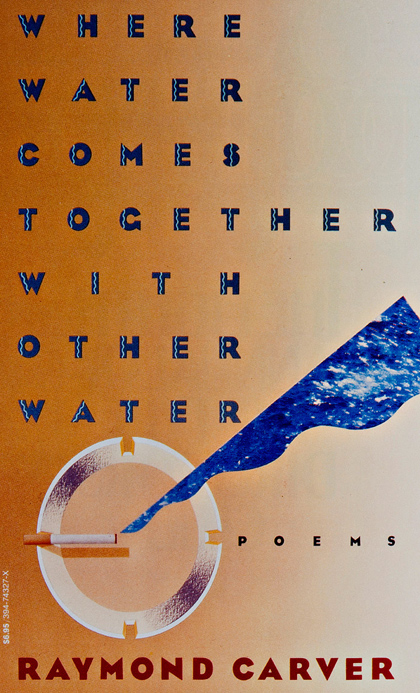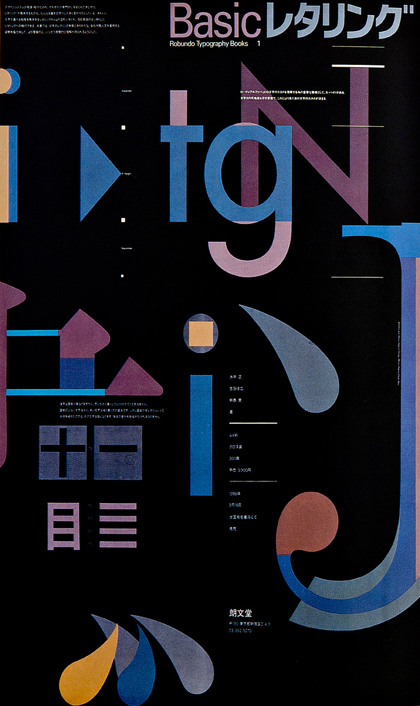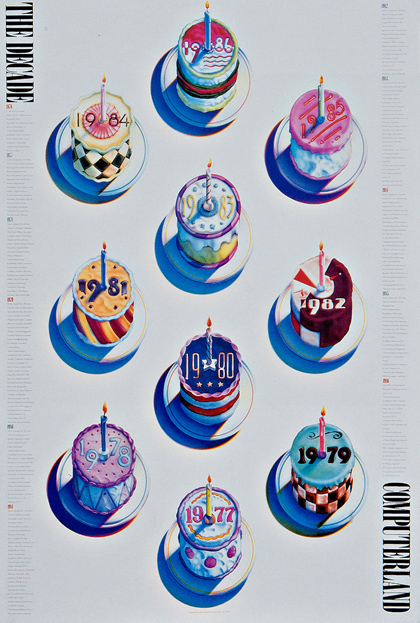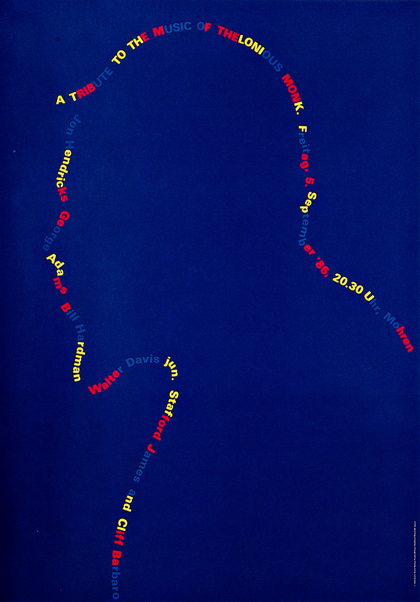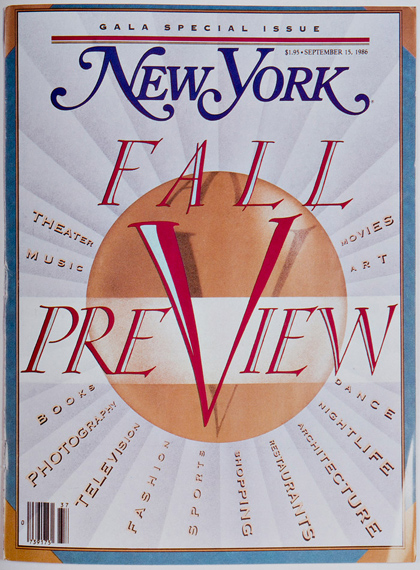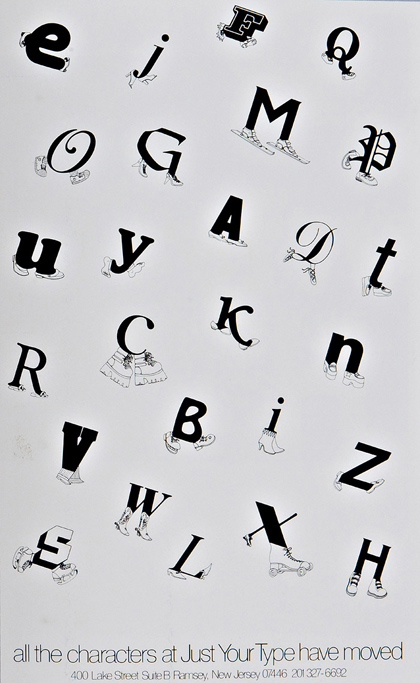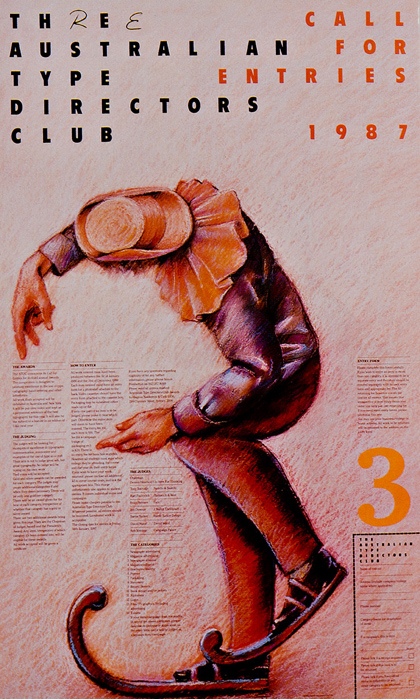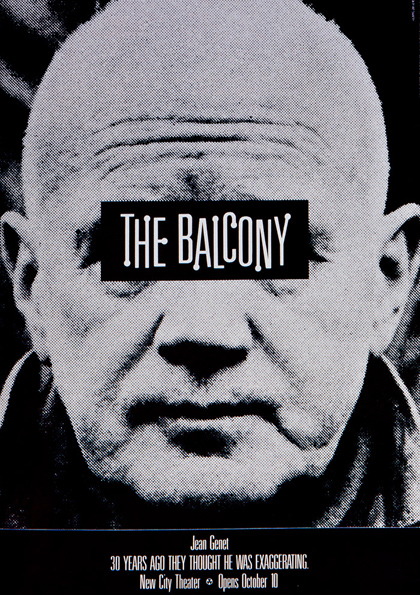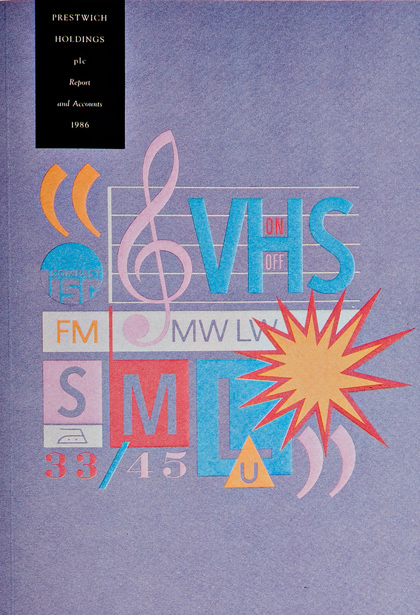
The Eighth Annual of The Type Directors Club | l’excellence typographique récompensée
La photo ci-dessus est le portrait d’Edward Benguiat, qui a présidé au Jury du 8e awards des Type Directors Club de New York en 1985. L’Annual des awards a été édité en ’86. Nous sommes donc bien 4 à 6 ans avant l’arrivée massive du langage PostScript qui allait révolutionner le monde des Arts Graphiques et d’une manière générale introduire le monde numérique d’aujourd’hui. Les travaux que vous allez voir sont donc tous réalisés de façon «traditionnelle». Est-ce à dire à la main? Non pas tout à fait.
Il existait déjà à l’époque des procédures de fabrications numériques. Mais les machines étaient aux mains d’une industrie (photocomposition, photogravure, retouches photos, épreuvages etc.) qui comptait «à la louche» environ 250.000 à 300.000 salariés dans le monde.
Par comparaison aujourd’hui, avec la propagation des technologies du numérique, vous pouvez mutiplier ce chiffre par 10 à 40 si vous voulez avoir une idée du nombre de personnes qui ont accès à ces technologies. Et c’est sans compter les nouvelles technologies qui apparaissent sur les smartphones qui proposent des applications à 0,79€.
Les travaux que vous allez voir ci-dessous ont été primés. Ils représentent ce qui se faisait de plus élégant, de plus efficace et de plus créatif aux yeux d’un jury très exigeant. Des tours de force de la création si l’on songe que les artistes devaient préparer des maquettes qui étaient exécutés ensuite par une «chaîne graphique» de professionnels qui travaillaient en ignorant ce qui était fait en amont et en aval.
J’ai rencontré Edward Benguiat à plusieurs reprises à Paris, Hambourg, Berlin et New York où il m’a invité dans un des restaus les plus agréables du quartier des publicitaires autour de la 42e rue. Pour mémoire je citerai l’une des ses créations les plus connues, la collection de caractère dit «Souvenir ITC» qui servit à Roger Excoffon pour la composition des feuilles de déclaration d’impôts de 73 (alors que Giscard d’Estaing était ministre des finances).